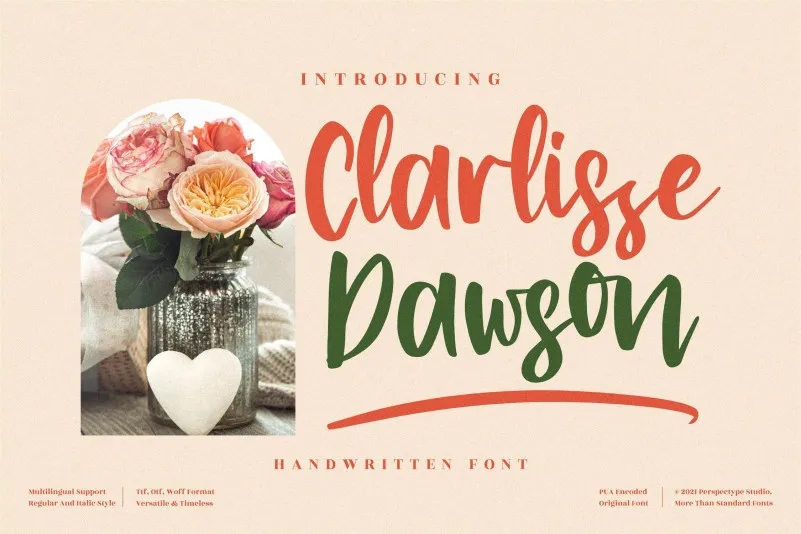
Clarlissa Dawson Font – Download Grátis
Essa é uma fonte cíntica, ou script, muito delicada e meticulosamente construída. Ideal para quem busca aperfeiçoamento e sofisticação em cada caractere, este fonte se destaca por seu detalhismo impressionante. Seja para anúncios de moda, letras d’arte para editoriais gráficas ou para qualquer tipo de design onde haja uma necessidade de elegância e sofisticação, essa font é certamente um ativo valioso para a sua biblioteca de fontes. Suas linhas fluidas e delicadas são capazes de enriquecer e dar vida a qualquer projeto, tornando-a uma escolha perfeita para qualquer tipo de criação visual requintada. Seja qual for o tema, essa fonte é certamente um tesouro a ser adicionado à sua coleção de recursos gráficos.